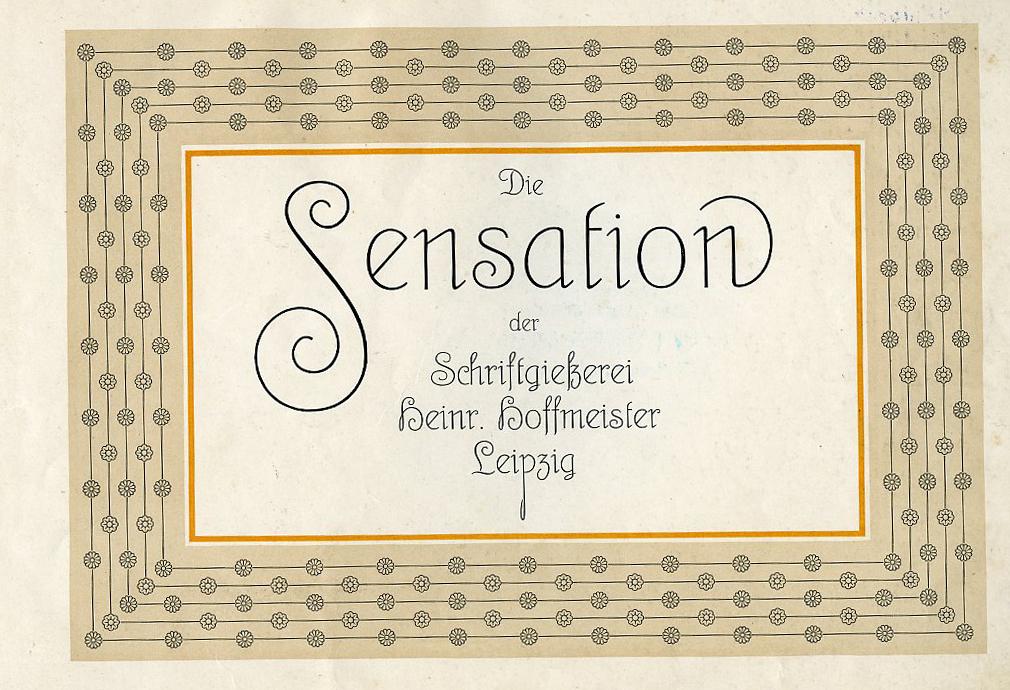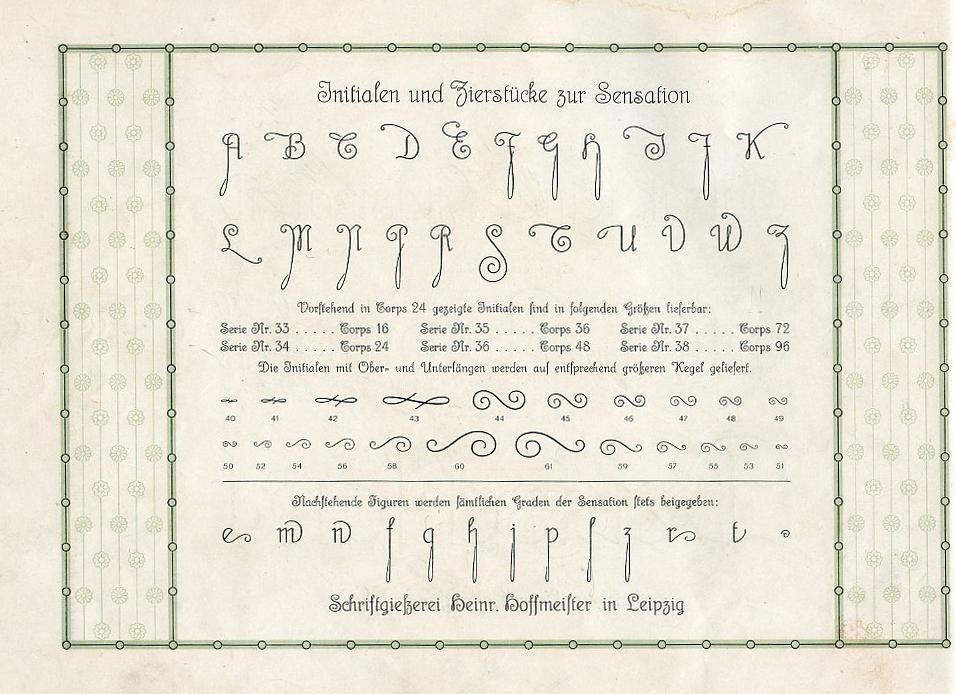
20er-Jahre-Schrift (?) mit langem s?
Eine Schrift darf bei der Aufzählung ähnlicher Typen nicht fehlen:
Die »Wolfram« von Hans Wagner, 1930 bei Ludwig & Mayer erschienen.
Hallo zusammen, ich bin auf die «Sensation» gestossen, ich habe die Schrift im Bleisatz in den Grössen 12, 16, 20 und 28 Punkt
Sie kam 1913 auf den Markt, ich habe dazu ein Musterbuch,
ich verwende sie für Namen bei Visitenkarten
Zudem habe ich die Schrift in zwei Grössen als Prägetypen in Messing.
Ich liebe die Schrift! Gruss Handdrucker
Das hatten wir doch schon vor längeren geklärt, Es ist die Sensation von D. Stempel, hier ein Bild aus dem damals gezeigten Schriftmuster:
Ich hätte die längst gern digitalisiert, nur ist das anhand eines Schriftmusters nicht so leicht, da ich kaum alle Figuren in einer Entwurfsgröße finde, und sich die Formen in den verschiedenen Entwurfsgrößen doch leider unterscheiden, da ist es schwer, das sauber hin zu bekommen. Am liebsten hätte ich daher einmal Fotos der Lettern aller Figuren, so wie ich sie vor einiger Zeit von dieser extremen Schnörkelschrift hatte.
Wirklich eine sehr schöne Schrift, und ein herrliches Musterheft. Die Alternativformen – als ob es damals schon Opentype gegeben hätte.
Aber zum Nachschöpfen braucht man m.E. nicht unbedingt einen kompletten Zeichensatz.
Zum Nachschöpfen™* wahrscheinlich nicht – zum Nachbauen wie Catfonts es macht wohl eher schon. Welches der richtigere oder bessere Ansatz ist, darüber sollte sich jeder seine eigene Meinung bilden ... :-?
Schönes Sortiment herrlich altmodischer Schriften, von denen ich mir so einige wohl genauer ansehen werde. Aber leider eben in recht geringer Auflösung, bei dem es dann eben doch auf ein Nachempfinden und Neuzeichnen heraus läuft.